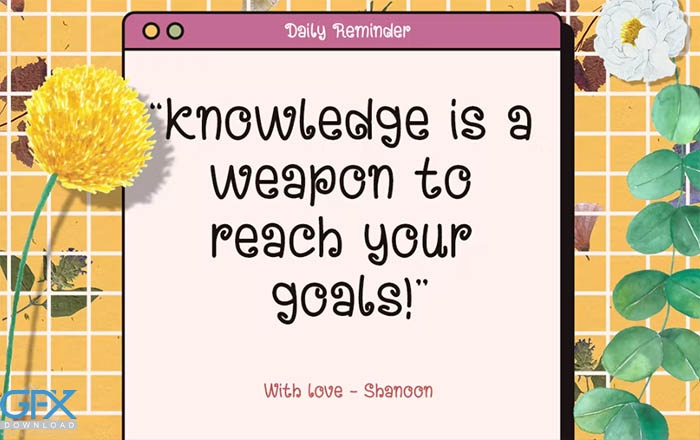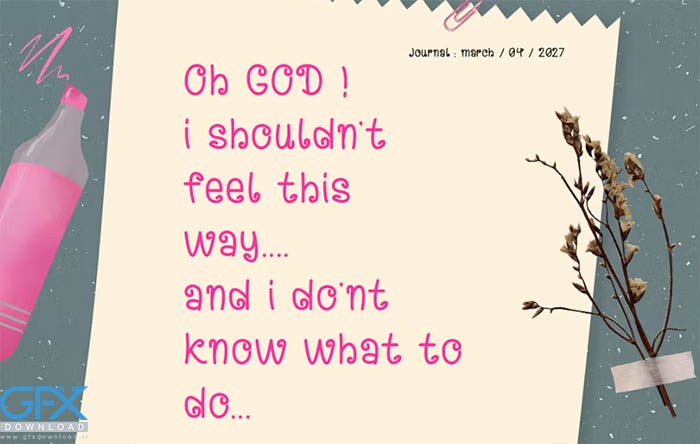
فونت فانتزی و دخترانه Swing Happy
یک فونت انگلیسی عالی برای توصیف احساس دخترانه و ظریف. فونت انگلیسی رایگان برای بازار کتاب های دخترانه، فونت های دفتر خاطرات و دیوار، پوستر رویداد، فونت لوازم مدرسه، پوستر، عنوان فیلم، جلد یوتیوب، تصاویر کوچک یوتیوب، جلد صفحه رسانه های اجتماعی و غیره... برای دانلود رایگان فونت دخترانه Swing Happy از جی اف ایکس دانلود به ادامه مطلب مراجعه کنید.
• پایه لاتین A-Z و a-z، اعداد، علائم نقطه گذاری